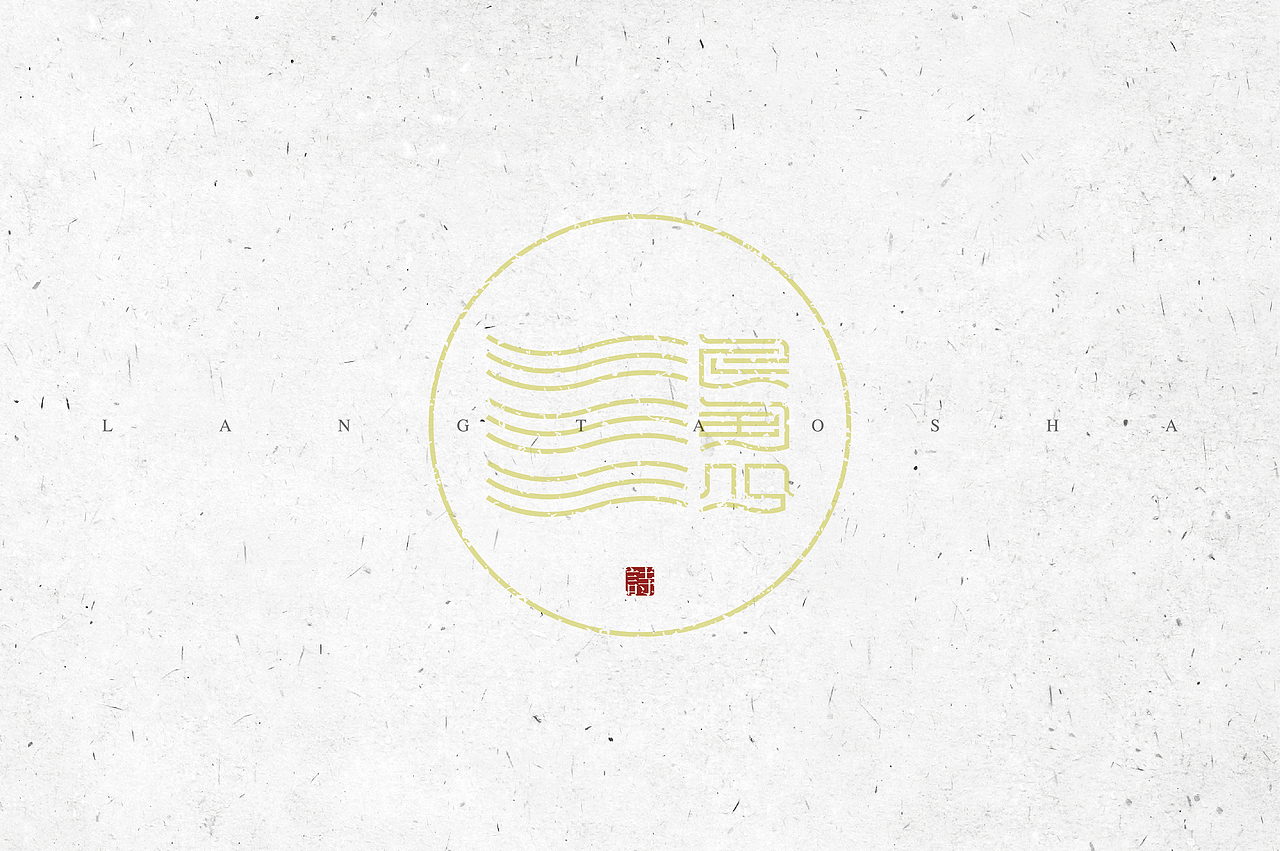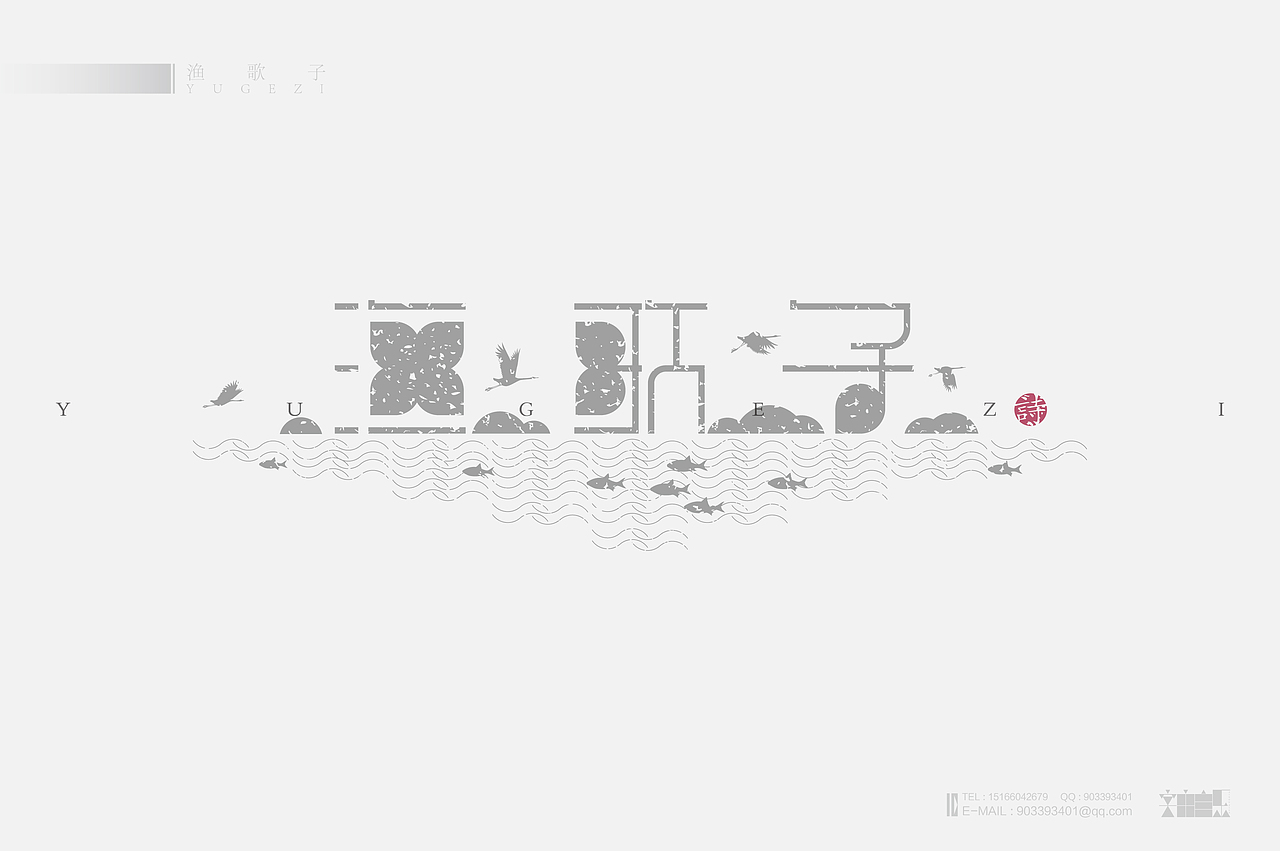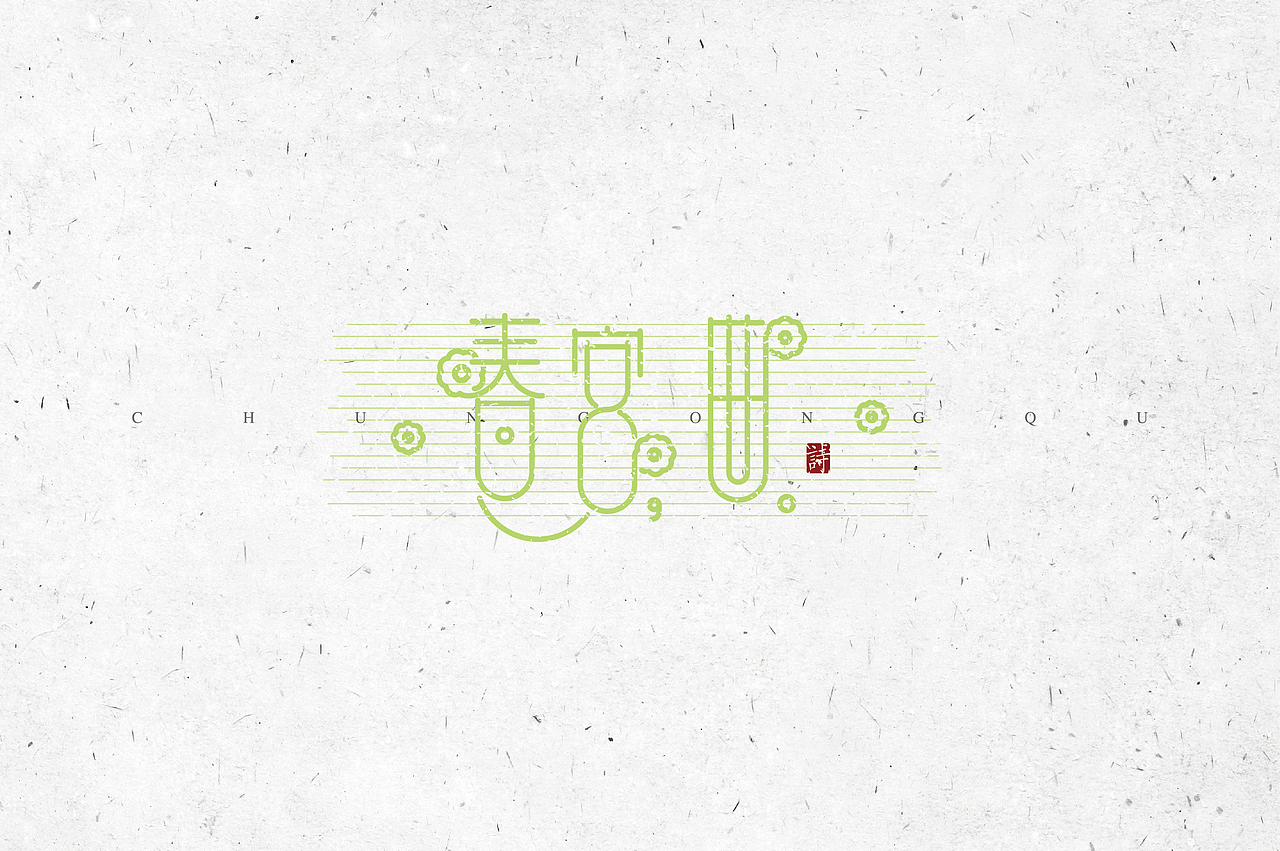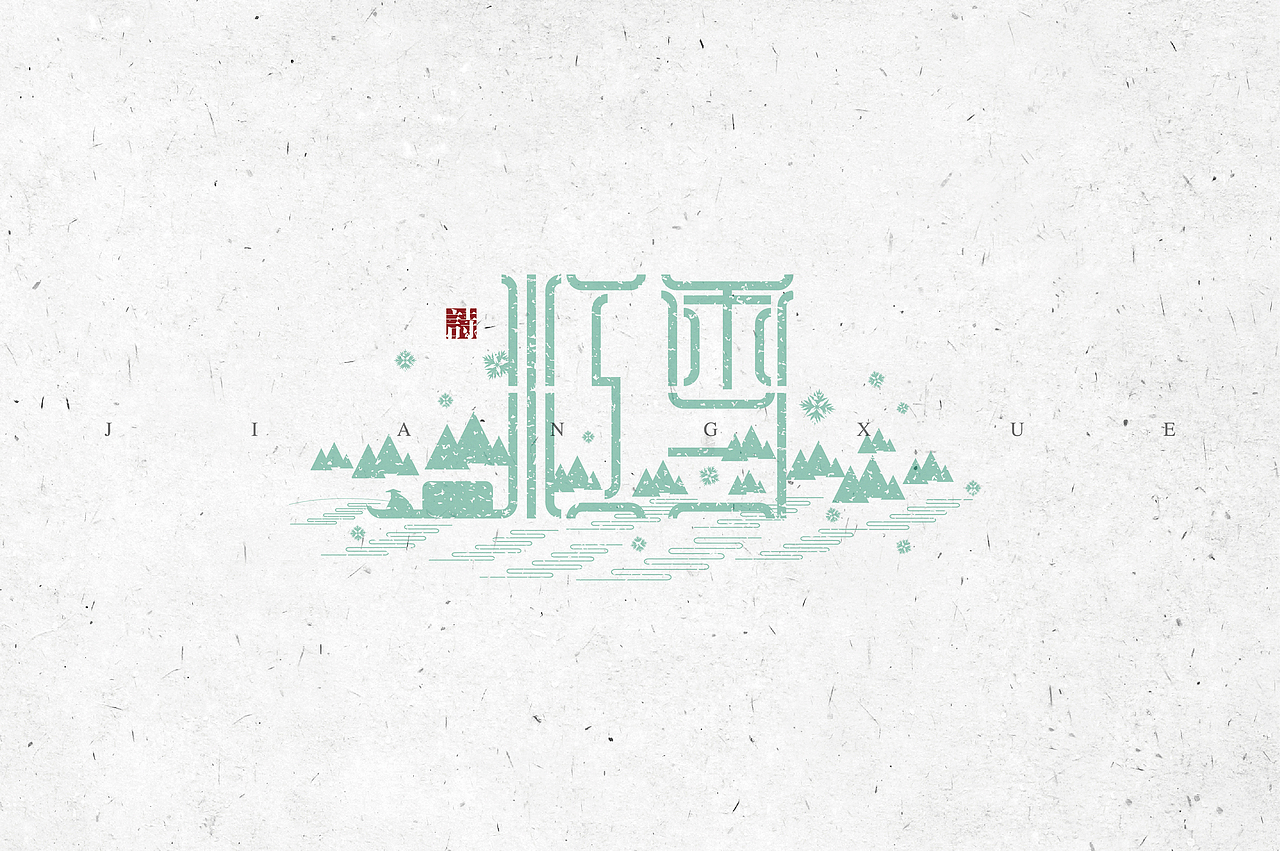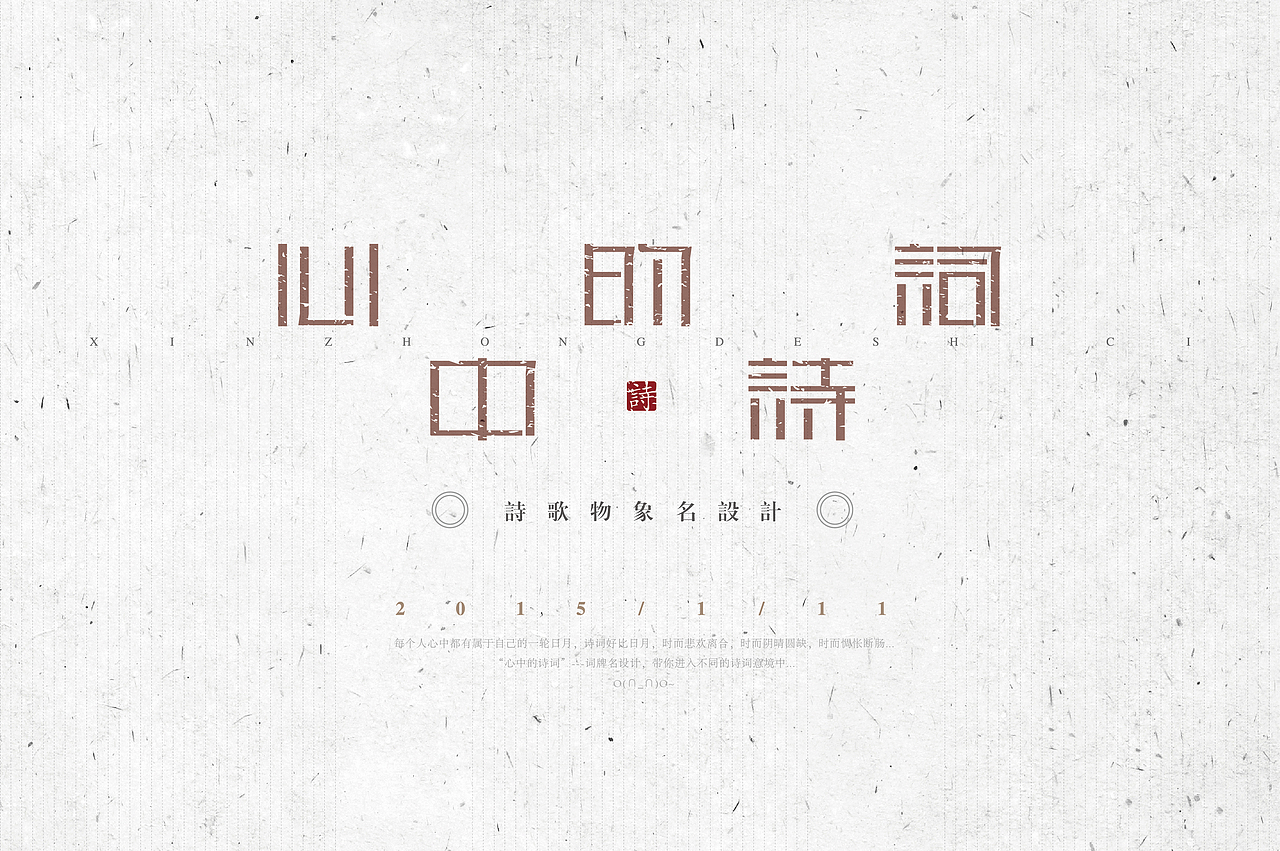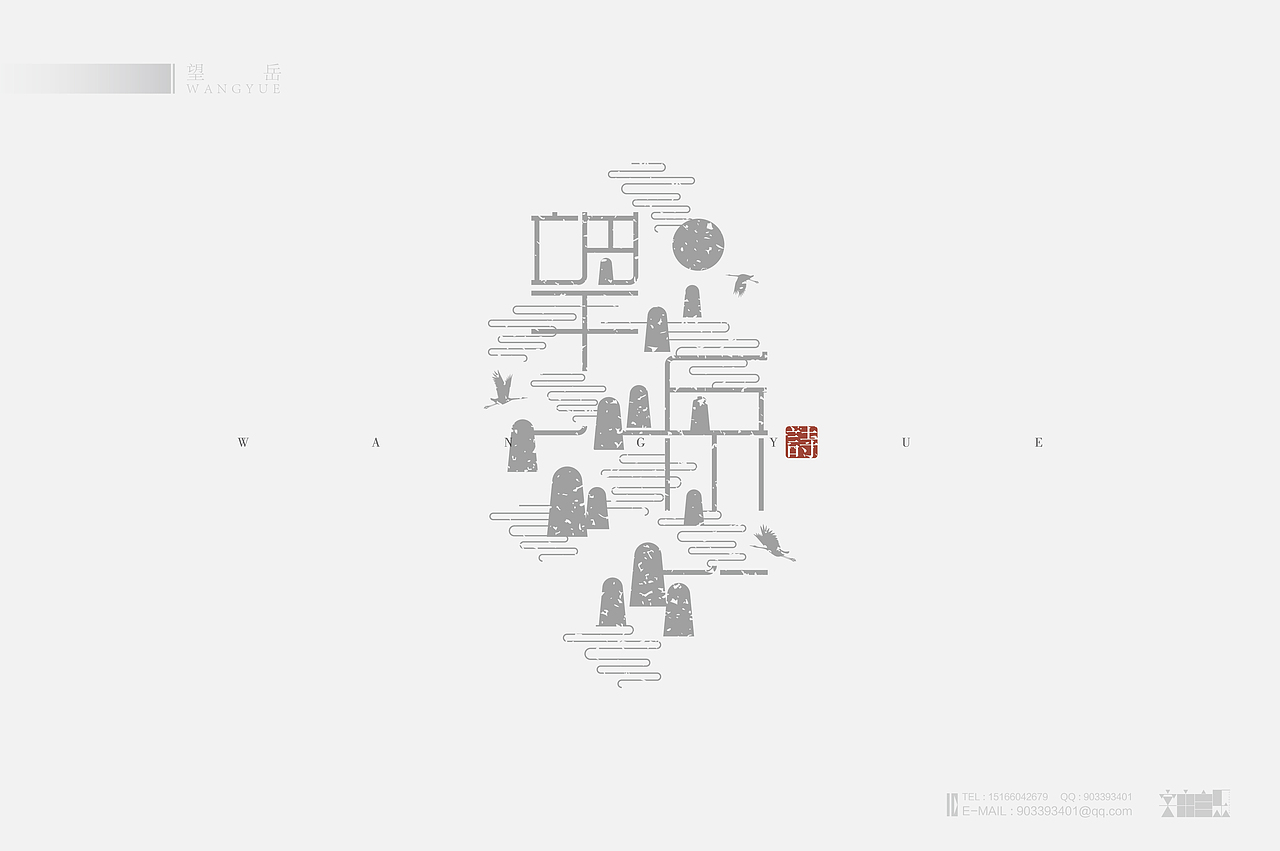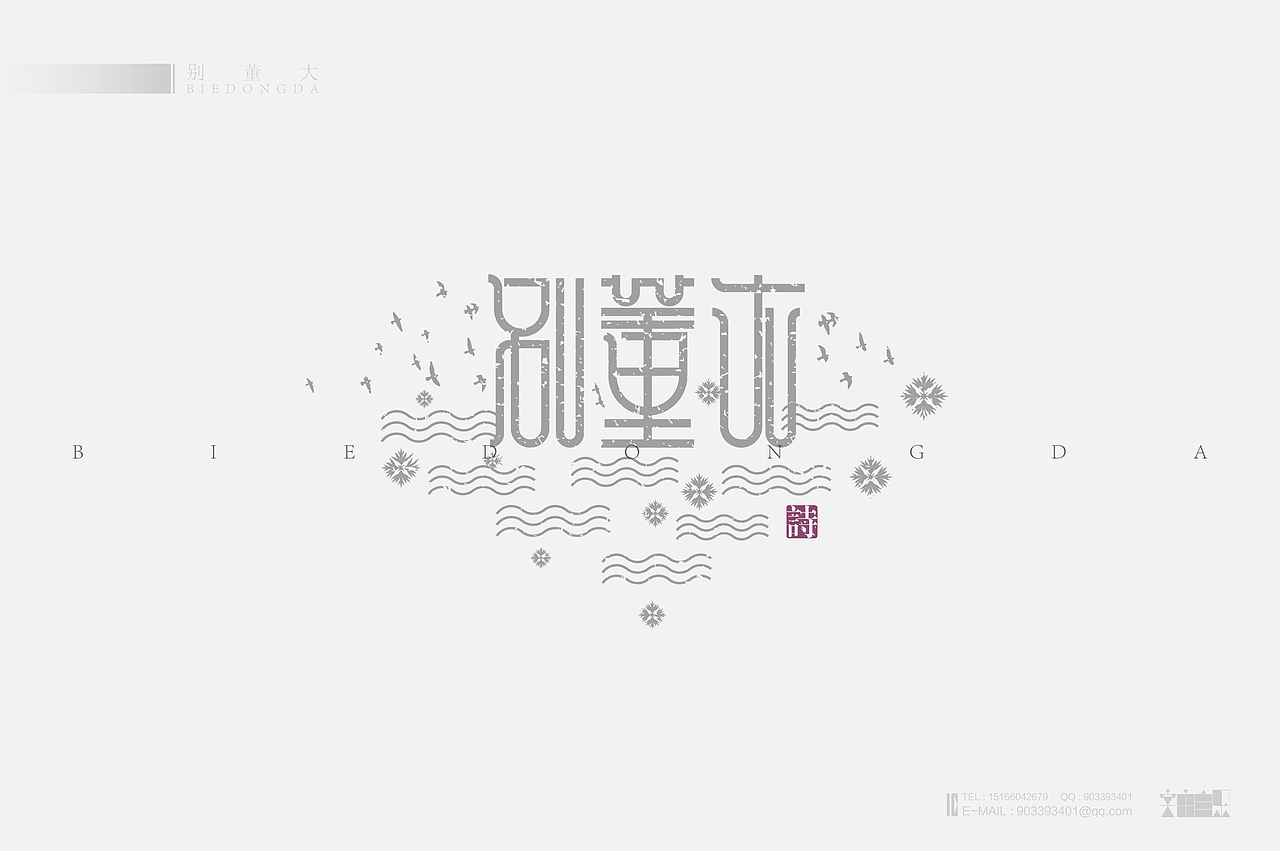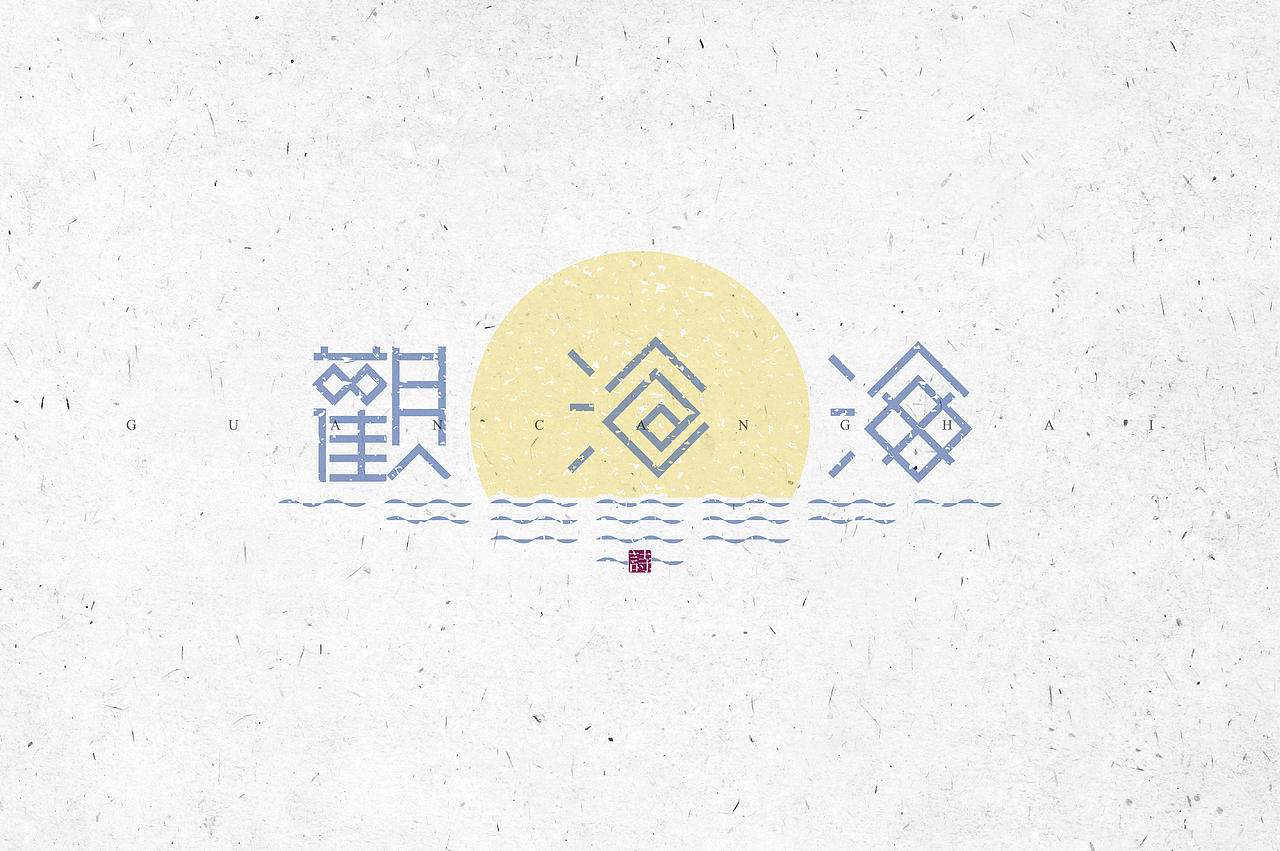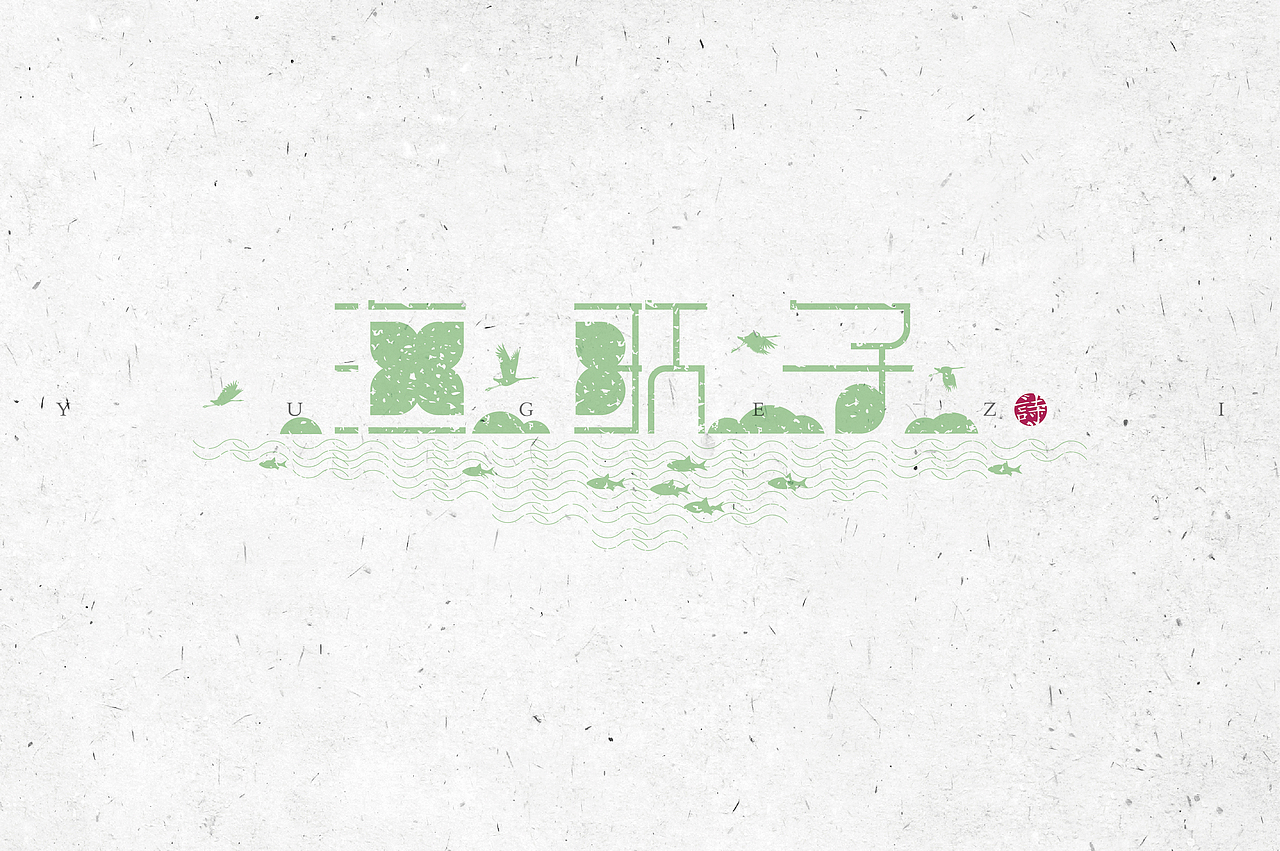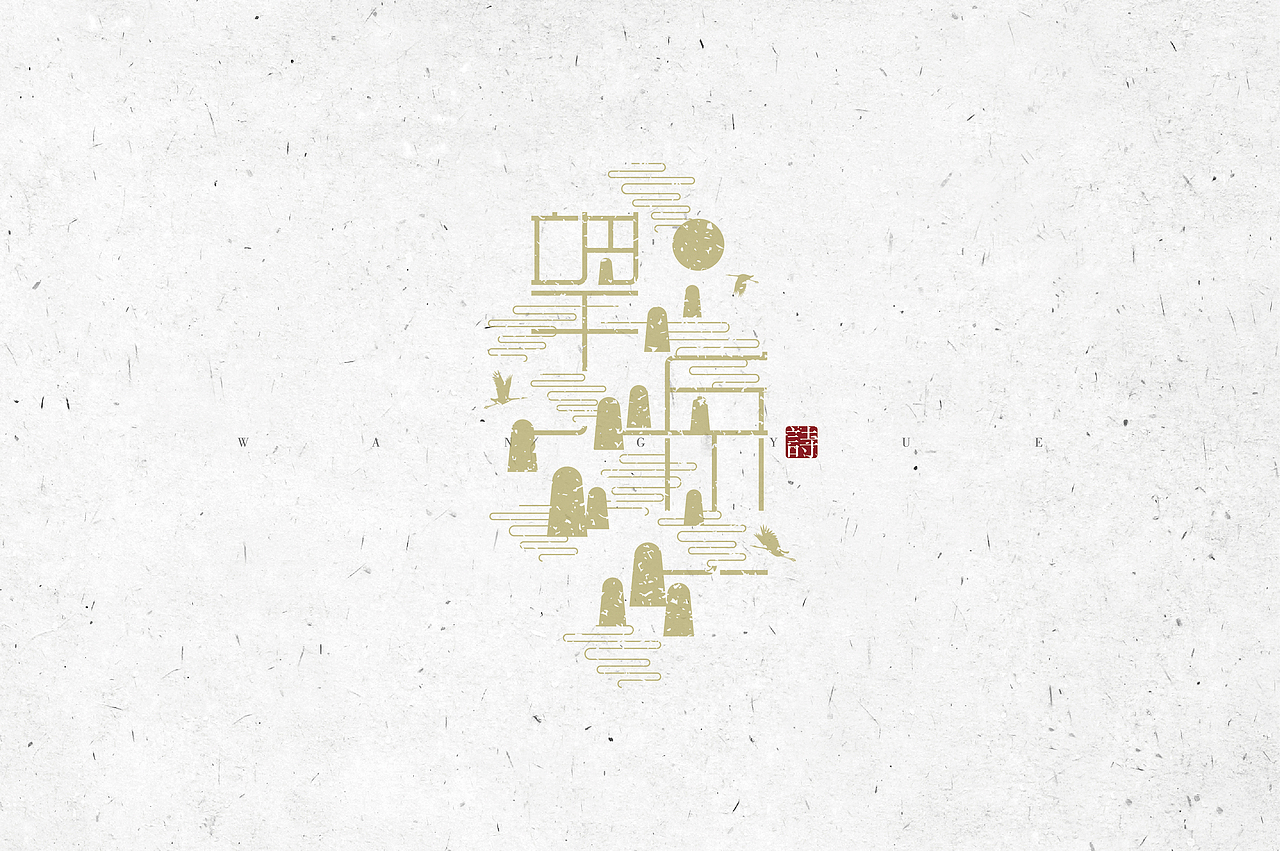
《“心中的诗词系列---物象诗歌名”设计》
“心中的诗词”系列,选取了20个记忆中耳熟能详描写物象的诗歌名,平日抽出时间,进行了设计...
“心中的诗词系列---物象诗歌名”设计,作为已在站酷网上一期发表的“心中的诗词系列---词牌名设计”(侧重点为词)的姊妹篇,“心中的诗词系列---物象诗歌名设计”选取的对象是描写物象的诗歌名(如描写“春天”的诗歌《春宫曲》),侧重点是诗...
物象即是客观事物,它不依赖于人的存在而存在,它有形状、颜色、声音、味道,是具体可感的。在文学术语里,物象,就是被作者人格化了的描写对象。作者塑造物象是为了言志、言情、言心...
天地山川,风云月露,花草叶木,鸟兽虫鱼,当这些具体事物寄托了作者某种特殊的意义时,这个物象就具有了“生命”,它是鲜活的、生动的...
因此,“物象诗歌名”以具象的含义居多,抽象含义的少一些...
此次“物象诗歌名”设计主要采取两种途径,融入现代设计形式进行设计。第一种途径:“物象诗歌名”具象含义的,如:观沧海(曹操征战途中观大海)、村居(春意盎然的农村生活图画)、春宫曲(春天宫中悦动的“乐”曲)、江雪(江山雪景垂钓美景图)、山居秋暝(山村秋雨之后绮旎的风光图)、忆江南(鲜艳夺目的江南春景图)...在物象诗歌名字义的基础上,以现代人的思维与艺术设计构成手法诠释;第二种途径:“物象诗歌名”抽象含义的,如:敕勒歌、将进酒、浪淘沙、渔歌子、望岳、别董大...在物象诗歌名字义的前提下,通过所选的与物象诗歌名相关的诗词,其所折射出来的意境,以现代人的思维与艺术设计构成手法阐述...
每个人心中都有属于自己的一轮日月,诗词好比日月,时而悲欢离合,时而阴晴圆缺,时而惆怅断肠...
“心中的诗词”系列开始,通过“物象诗歌名"的代表诗词(与“物象诗歌名"设计惜惜相关)一同带你进入不同的诗词意境中...
《每个人心中都有属于自己的一轮日月,诗词好比日月,时而悲欢离合,时而阴晴圆缺,时而惆怅断肠...“心中的诗词系列---物象诗歌名”设计(墨稿汇总),一共二十个,进行了诠释跟设计...》
《江雪》
《“心中的诗词”系列---江雪:描写物像:冬天。选取的代表作是唐代柳宗元的《江雪》,“千山鸟飞绝,万径人踪灭。孤舟蓑笠翁,独钓寒江雪。”这是一首五言山水诗,描述了一幅冰天雪地寒江,没有行人、飞鸟,只有一位老翁独处孤舟,默然垂钓的一幅江乡雪景图。山山是雪,路路皆白。飞鸟绝迹,人踪湮没。通过此幅渔翁寒江独钓图,表现了诗人永贞革新失败后,虽处境孤独,但仍傲岸不屈的性格...O(∩_∩)O~》
《小池》
《“心中的诗词”系列---小池:描写物像:夏天。选取的代表作是宋代杨万里的《小池》,“泉眼无声惜细流,树阴照水爱晴柔。小荷才露尖尖角,早有蜻蜓立上头。”《小池》是宋朝诗人杨万里的著名诗篇,这首诗通过对小池中的泉水、树阴、小荷、蜻蜓的描写,描绘出一种具有无限生命力的朴素、自然,而又充满生活情趣的唯美画面,表现了作者热爱生活的真挚感情...O(∩_∩)O~》
《观沧海》
《“心中的诗词”系列---观沧海:描写物像:大海。选取的代表作是魏晋曹操的《观沧海》,“东临碣石,以观沧海。水何澹澹,山岛竦峙。树木丛生,百草丰茂。秋风萧瑟,洪波涌起。日月之行,若出其中。星汉灿烂,若出其里。幸甚至哉,歌以咏志...”这首四言诗借诗人登山望海所见到的自然景物,描绘了祖国河山的雄伟壮丽,既刻画了高山大海的动人形象,更表达了诗人豪迈乐观的进取精神...O(∩_∩)O~》
《鹅鹅鹅》
《“心中的诗词”系列---鹅:描写物像:鹅。选取的代表作是初唐骆宾王的《鹅》,“鹅,鹅,鹅, 曲项向天歌。白毛浮绿水,红掌拨清波。”这首诗相传是骆宾王在七岁时写的一首诗,这是一首咏物诗。这首千古流传的诗歌,没有什么深刻的思想内涵和哲理,而是以清新欢快的语言,抓住事物(鹅)的突出特征来进行描写,写得自然、真切、传神...O(∩_∩)O~》
《山居秋暝》
《“心中的诗词”系列---山居秋暝:描写物像:秋天。选取的代表作是唐代王维的《山居秋暝》,“空山新雨后,天气晚来秋。明月松间照,清泉石上流。竹喧归浣女,莲动下渔舟。随意春芳歇,王孙自可留。”这是一首写山水的名诗,于诗情画意中寄托诗人的高洁情怀和对理想的追求。全诗描绘了秋雨初晴后傍晚时分山村的旖旎风光和山居村民的淳朴风尚,表现了诗人寄情山水田园,对隐居生活怡然自得的满足心情...O(∩_∩)O~》
《将进酒》
《“心中的诗词”系列---将进酒:描写物像:酒。选取的代表作是盛唐李白的《将进酒》,“君不见,黄河之水天上来,奔流到海不复回。君不见,高堂明镜悲白发,朝如青丝暮成雪。人生得意须尽欢,莫使金樽空对月。天生我材必有用,千金散尽还复来...”这首诗形象的表现了李白桀骜不驯的性格:一方面对自己充满自信,孤高自傲;一方面在政治前途出现波折后,又流露出及时行乐的消极思想...O(∩_∩)O~》
《村居》
《“心中的诗词”系列---村居:描写物像:乐春图。选取的代表作是清代高鼎的《村居》,“草长莺飞二月天,拂堤杨柳醉春烟。儿童散学归来早,忙趁东风放纸鸢。”诗意图《村居》描写出了一幅春天孩子们在村旁的芳草地上放风筝的图画,是一幅自然景物和活动着的人物融合在一起的、充满生机、春意盎然的农村生活图画。全诗字里行间透露出诗人对春天来临的喜悦和赞美...O(∩_∩)O~》
《浪淘沙》
《“心中的诗词”系列---浪淘沙:描写物像:黄河。选取的代表作是唐代刘禹锡的《浪淘沙》,“九曲黄河万里沙,浪淘风簸自天涯。如今直上银河去,同到牵牛织女家。”这首绝句模仿淘金者的口吻,表明他们对淘金生涯的厌恶和对美好生活的向往。同是在河边生活,牛郎织女生活的天河恬静而优美,黄河边的淘金者却整天在风浪泥沙中讨生活。直上银河,同访牛郎织女,寄托了他们心底对宁静的田园牧歌生活的憧憬...O(∩_∩)O~》
《敕勒歌》
《“心中的诗词”系列---敕勒歌:描写物像:阴山。选取的代表作是南北朝斜率敦的《敕勒歌》,“敕勒川,阴山下。天似穹庐,笼盖四野。天苍苍,野茫茫。风吹草低见牛羊。”这首北朝民歌,虽然仅有二十七个字,却有极大的艺术感染力。它歌咏了北国草原的富饶、壮丽,抒发了敕勒人对养育他们的水土,对游牧生活无限热爱之情...O(∩_∩)O~》
《墨梅》
《“心中的诗词”系列---墨梅:描写物像:梅花。选取的代表作是元代王冕的《墨梅》,“我家洗砚池边树,朵朵花开淡墨痕。不要人夸好颜色,只留清气满乾坤”。这是一首题画诗。诗人赞美墨梅不求人夸,只愿给人间留下清香的美德,实际上是借梅自喻,表达自己对人生的态度以及不向世俗献媚的高尚情操。 这首诗题为“墨梅”,意在述志。诗人将画格、诗格、人格有机地融为一体...O(∩_∩)O~》
《望岳》
《“心中的诗词”系列---望岳:描写物像:泰山。选取的代表作是唐代王维的《望岳》,“岱宗夫如何?齐鲁青未了。造化钟神秀,阴阳割昏晓。荡胸生曾云,决眦入归鸟。会当凌绝顶,一览众山小。”这首诗通过描绘泰山雄伟磅礴的气象,热情赞美了泰山高大巍峨的气势和神奇秀丽的景色,流露出了对祖国山河的热爱之情,表达了诗人不怕困难、敢攀顶峰、俯视一切的雄心和气概,以及卓然独立、兼济天下的豪情壮志...O(∩_∩)O~》
《静夜思》
《“心中的诗词”系列---静夜思:描写物像:月亮。选取的代表作是盛唐李白的《静夜思》,“床前明月光,疑是地上霜。举头望明月,低头思故乡。”这首诗写远客思乡之情,诗以明白如话的语言雕琢出明静醉人的秋夜的意境。它不追求想象的新颖奇特,也摒弃了辞藻的精工华美;它以清新朴素的笔触,抒写了丰富深曲的内容。境是境,情是情,那么逼真,那么动人,百读不厌,耐人寻绎...O(∩_∩)O~》
《“心中的诗词系列---物象诗歌名”设计(汇总),O(∩_∩)O...》